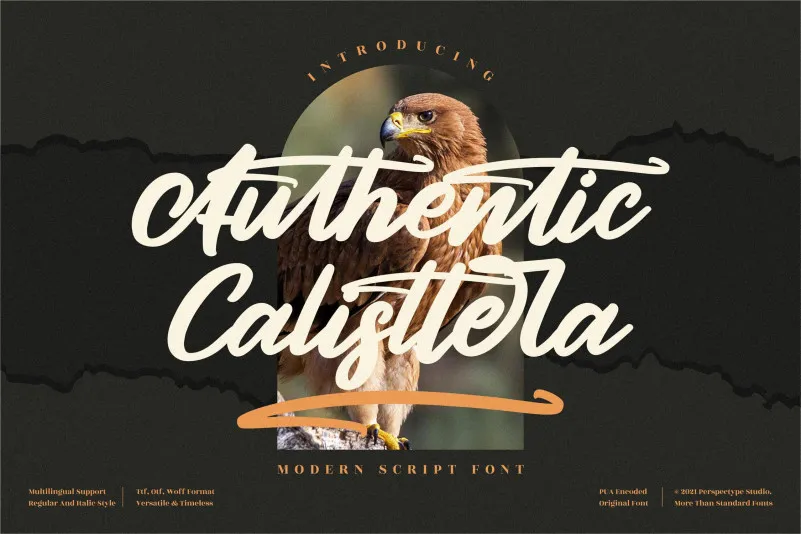
Esta é uma fonte script moderna e desenhada com traços fortes e suavizados. Ela se destaca para os projetos que precisam de um estilo pessoal, como convites de casamento, cartões de agradecimento, anúncios de casamentos, cartões de boas-vindas, logotipos e muito mais. Esta font PUA está codificada, o que significa você pode acessar facilmente todos os gílios e swashes. Sua elegância e sofisticação a tornam uma opção perfeita para qualquer projeto que deseje transmitir um estilo único e sofisticado. Perfect para adicionar um toque personalizado em sua próxima criação gráfica.